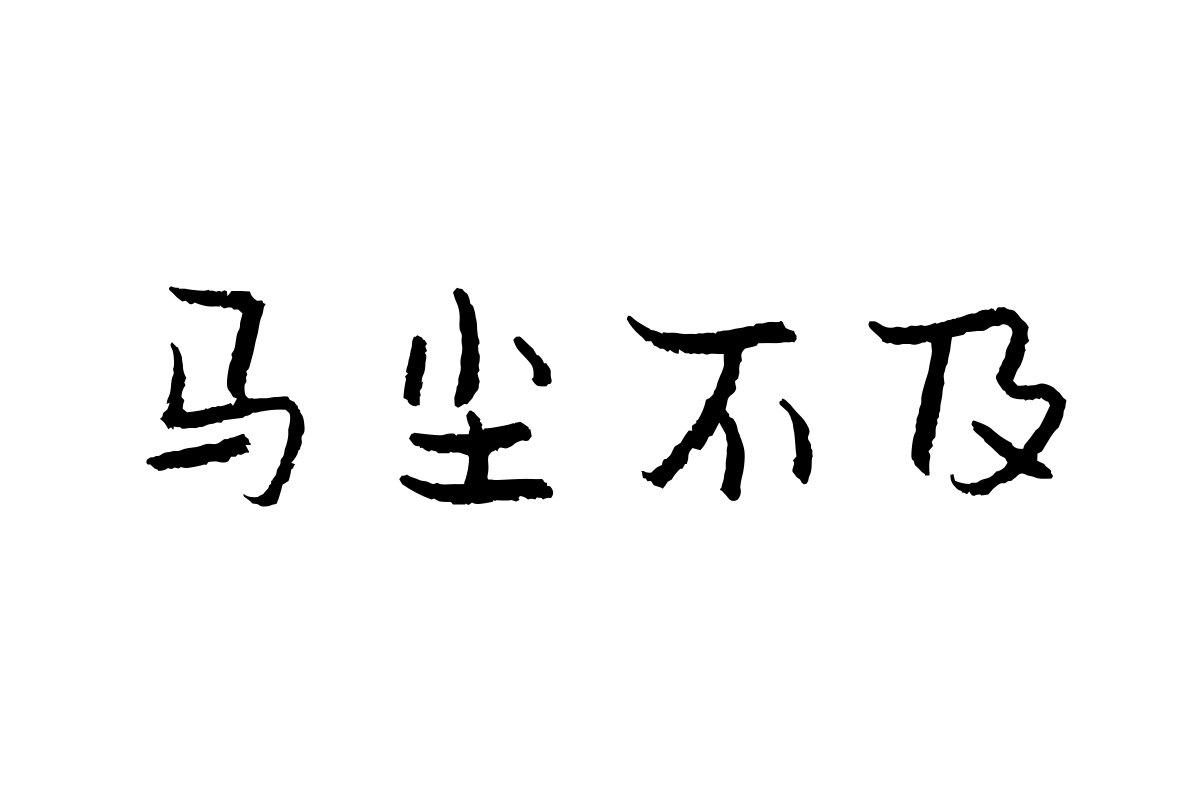
汉仪尚巍小顽童是一款现代简约风格的中文字体,具有独特的艺术感和设计感。这款字体采用了简洁的笔画和结构,使得文字看起来更加清晰易读,同时也具有很强的视觉冲击力。
汉仪尚巍小顽童字体的特点在于其独特的艺术风格,线条流畅而有力,给人一种活泼、灵动的感觉。同时,这款字体也具有较强的个性和辨识度,能够很好地表达出设计师想要传达的主题和情感。
总的来说,汉仪尚巍小顽童是一款非常适合现代设计需求的中文字体,无论是用于网页设计、平面设计还是其他需要文字的地方,都能展现出其独特的魅力。
汉仪尚巍小顽童